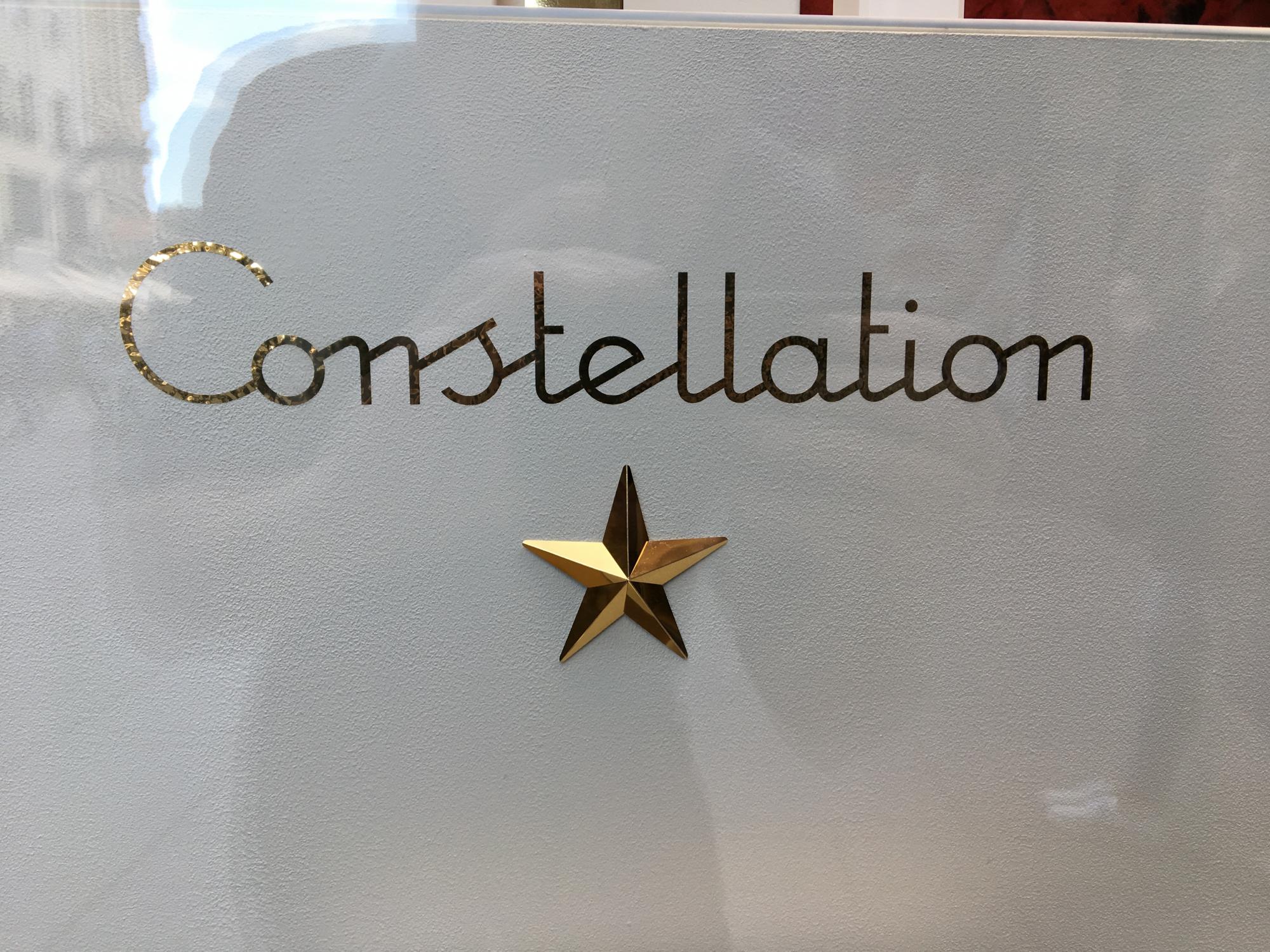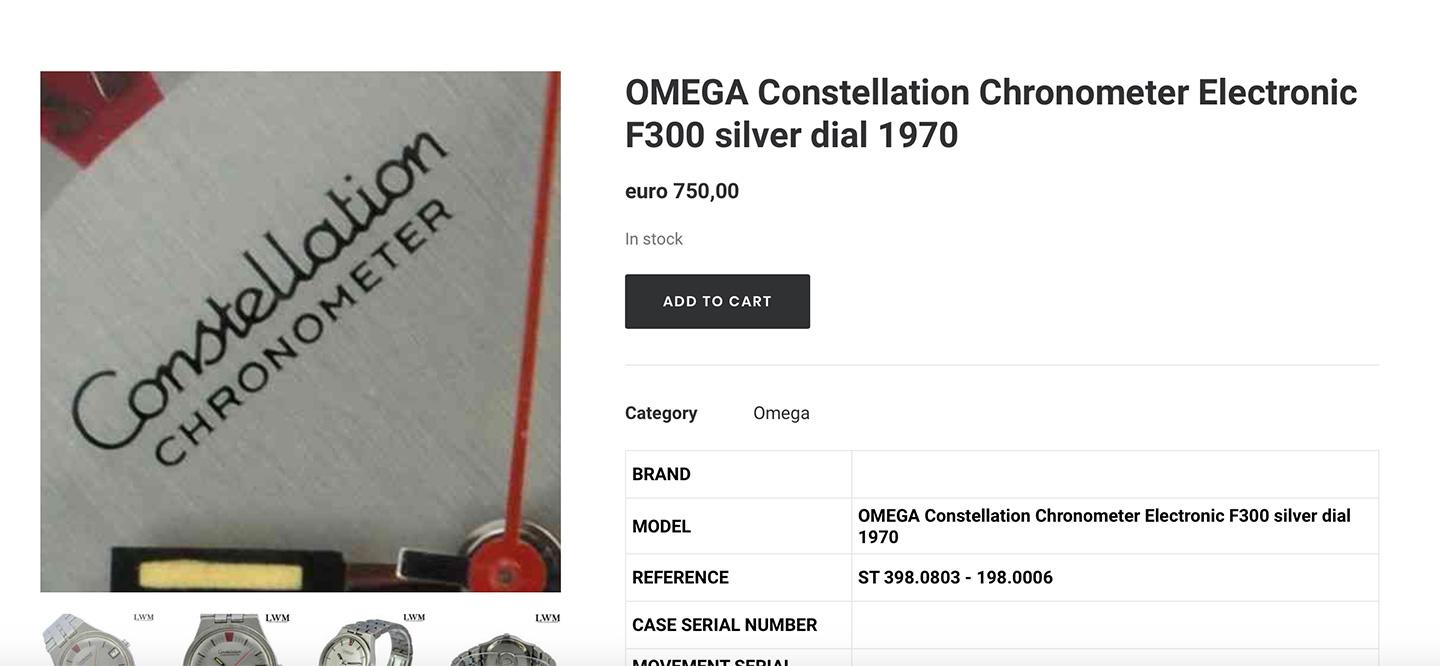
Suche Schriftart von Omega Constellation
ich suche diese elegante Schriftart die ich im Schaufenster von Omega (Uhrenhersteller) gesehen habe.
Dabei wird es sich vermutlich eher um den typografischen Nachbau des alten "OMEGA Constellation" Schriftzugs handeln, als um eine lizenzierbare Satzschrift. (Screenshot von hier)
Nachtrag: Wenn man in dem PDF der OMEGA-Presseinformation sucht, findet man auch dort nur die Vektoren des modernisierten Schriftzugs/Logos (S.60/61).